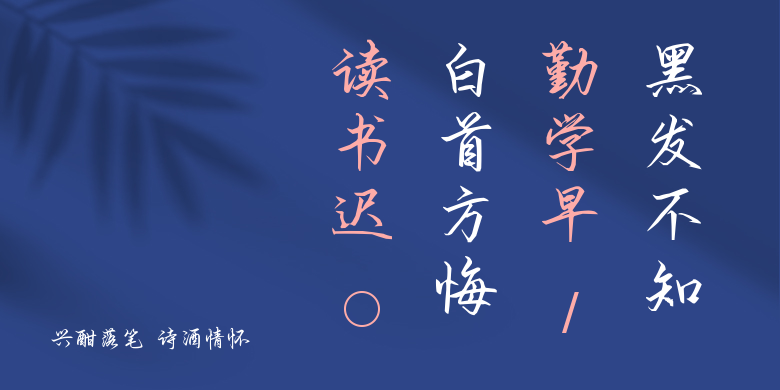
兴酣落笔 诗酒情怀
兴酣落笔 诗酒情怀,这款字体结构工整、笔画清晰,兼顾美观与易读性,适用于标题、正文、海报、包装、LOGO 等多种场景。字形优雅稳定,风格百搭耐看,适配日常排版与创意设计,让文字呈现更舒适、更具质感。兴酣落笔 诗酒情怀一笔一画,皆是细节,以均衡的比例、流畅的线条打造舒适视觉体验,字形端正大气,风格简约现代。无论是商业设计、品牌宣传还是日常排版,都能轻松驾驭,让文字更有格调与力量。兴酣落笔 诗酒情怀字体下载。